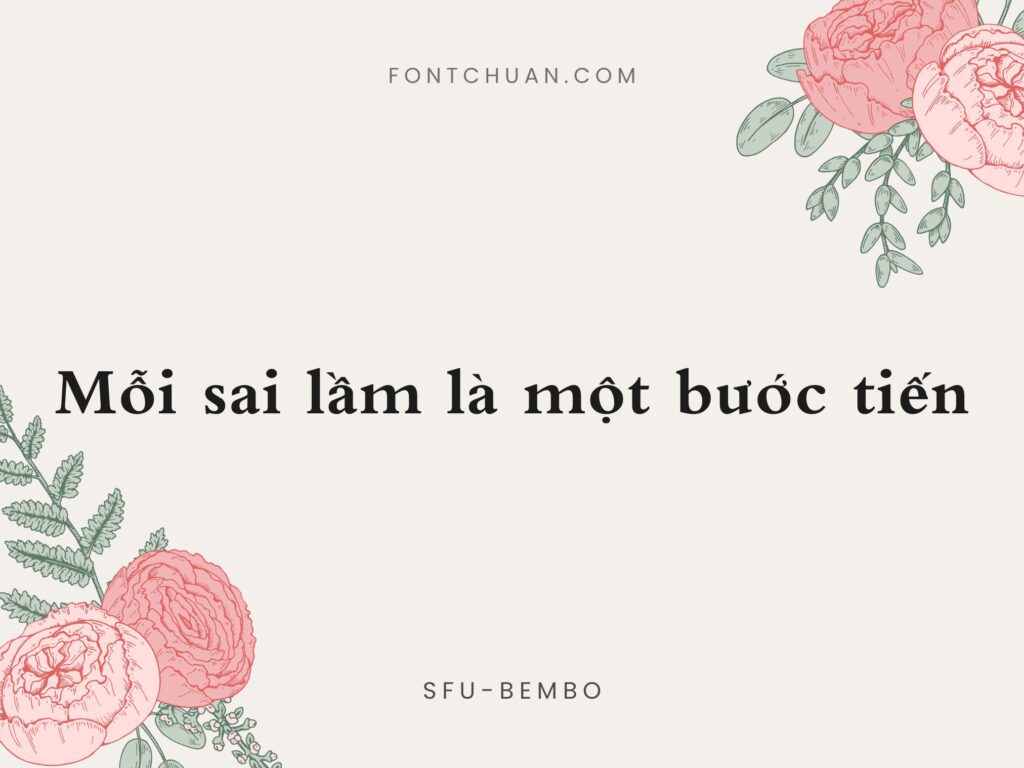
Font Bembo là một kiểu chữ serif cổ điển, được thiết kế bởi Francesco Griffo vào năm 1495 và được hồi sinh bởi Stanley Morison vào năm 1929. Với nguồn gốc từ thời kỳ Phục hưng Ý, Bembo mang lại sự tinh tế và thanh lịch, phù hợp cho nhiều mục đích thiết kế khác nhau như in ấn, xuất bản và thiết kế kỹ thuật số. Font này hỗ trợ đầy đủ tiếng Việt, giúp người dùng dễ dàng ứng dụng trong các dự án đa ngôn ngữ
Về đặc điểm thiết kế, Bembo thuộc nhóm font serif với các nét chữ mềm mại nhưng vẫn rõ ràng, tạo cảm giác dễ đọc và thu hút. Kiểu chữ này rất phù hợp để sử dụng trong các thiết kế như sách, tạp chí, thiệp mời, logo và các ấn phẩm quảng cáo